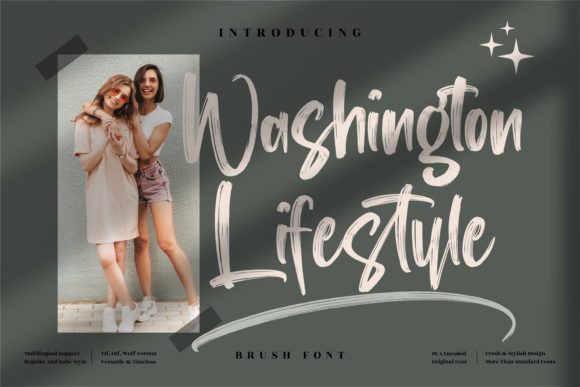
Creativefabrica Washington Lifestyle Font
[Creativefabrica] Washington Lifestyle Font
Washington Lifestyle - это причудливый шрифт с матовым начертанием, выполненный в непринужденной тематике и отличающийся прекрасным стилем.